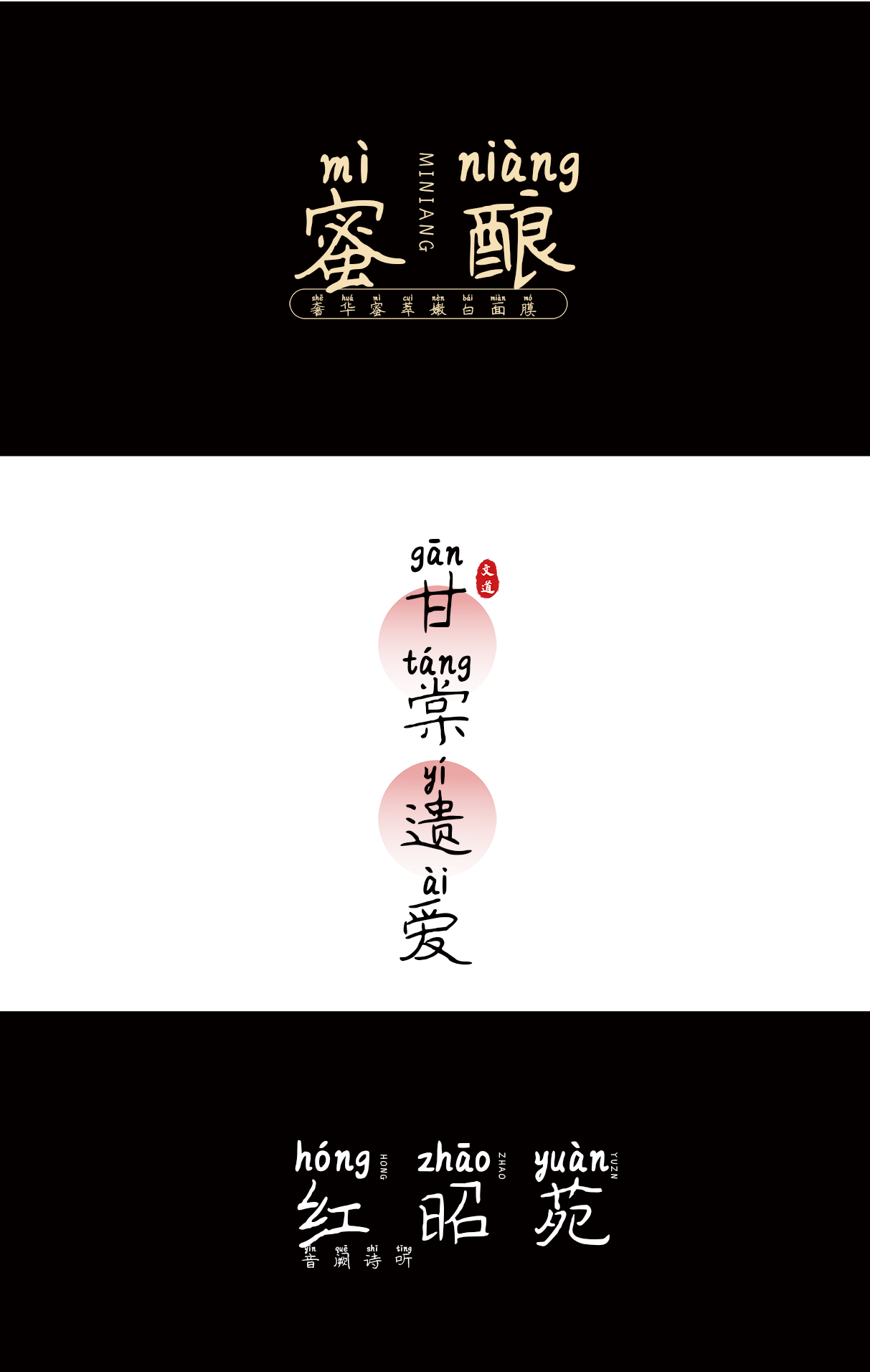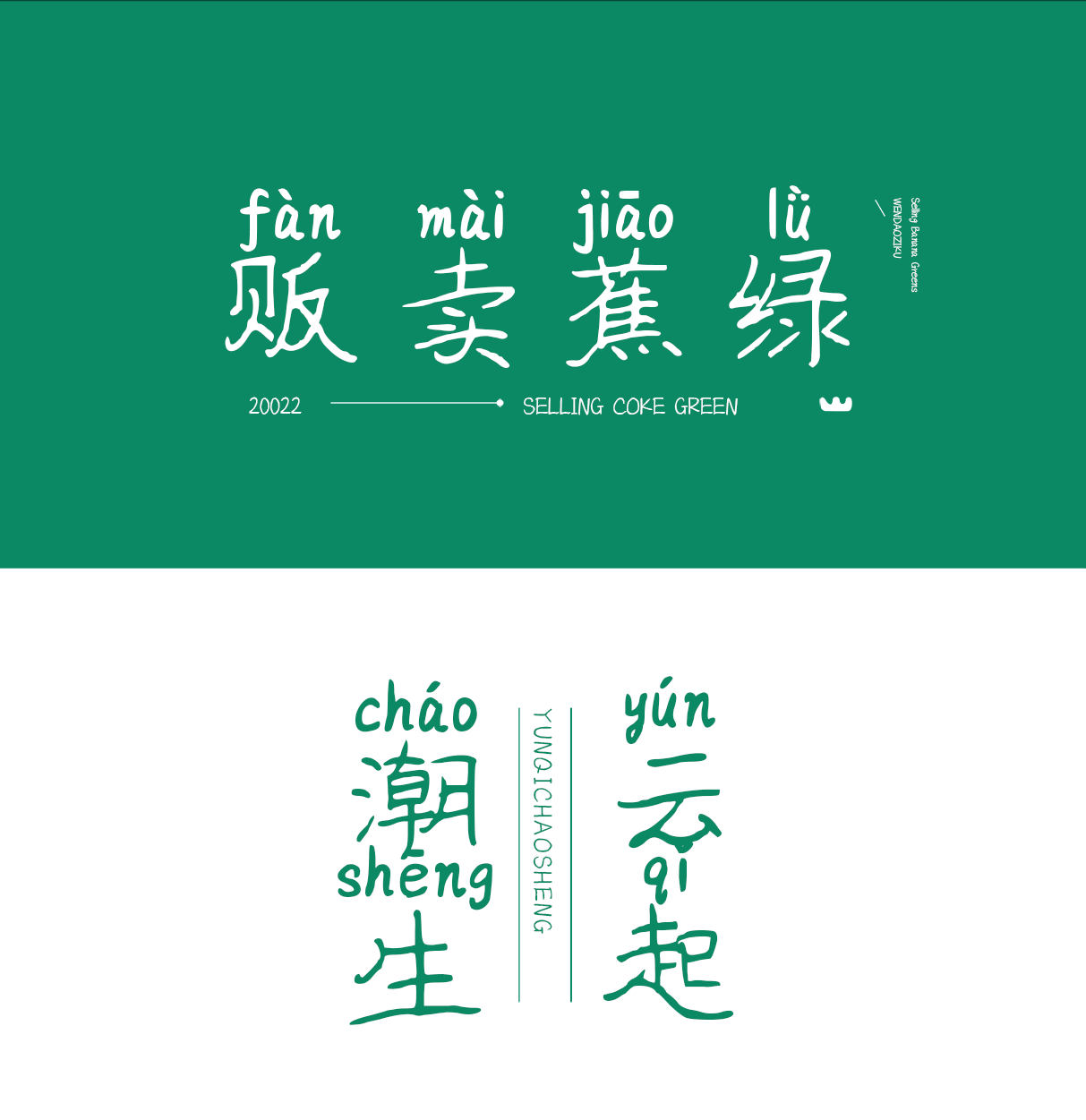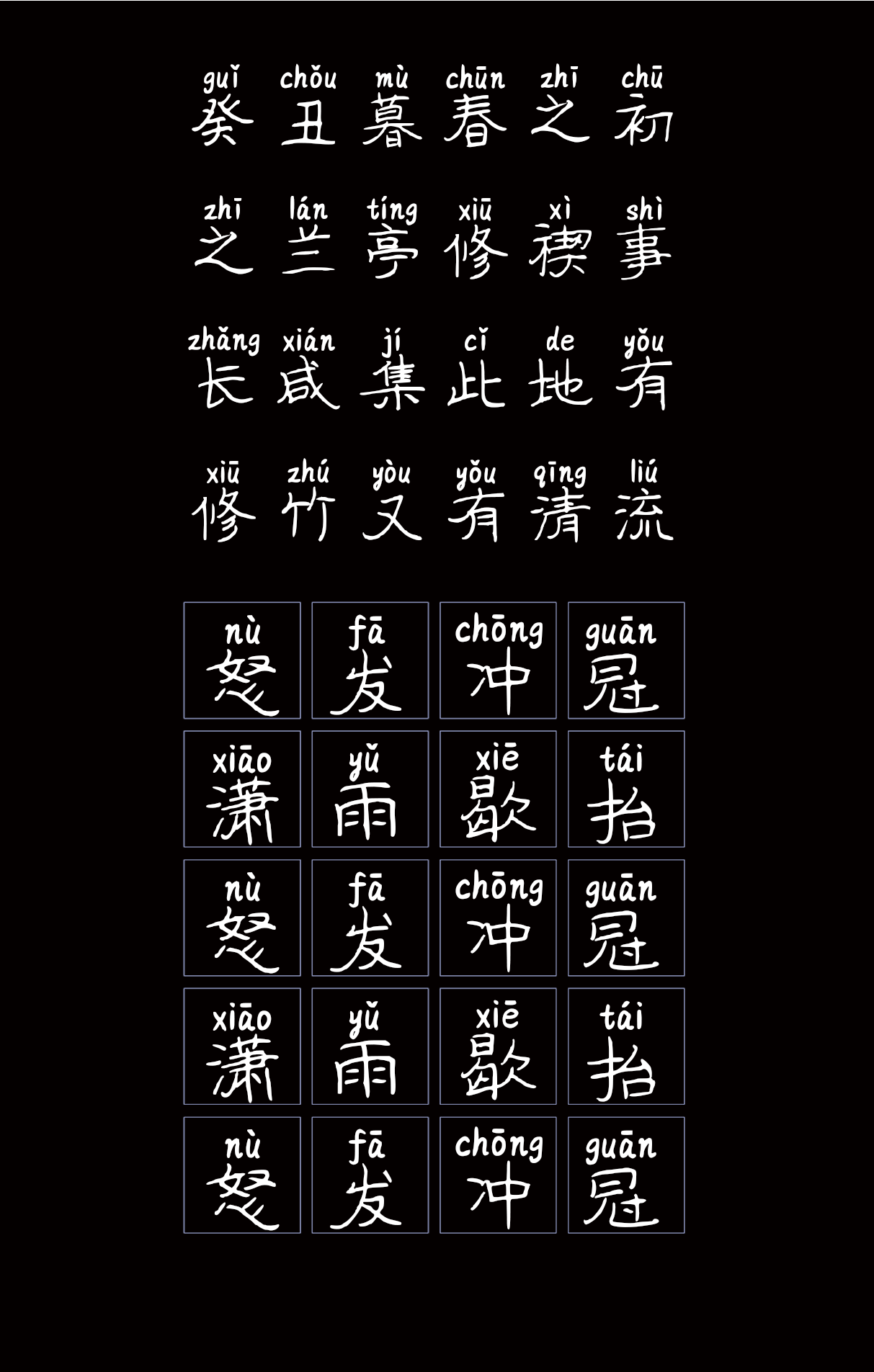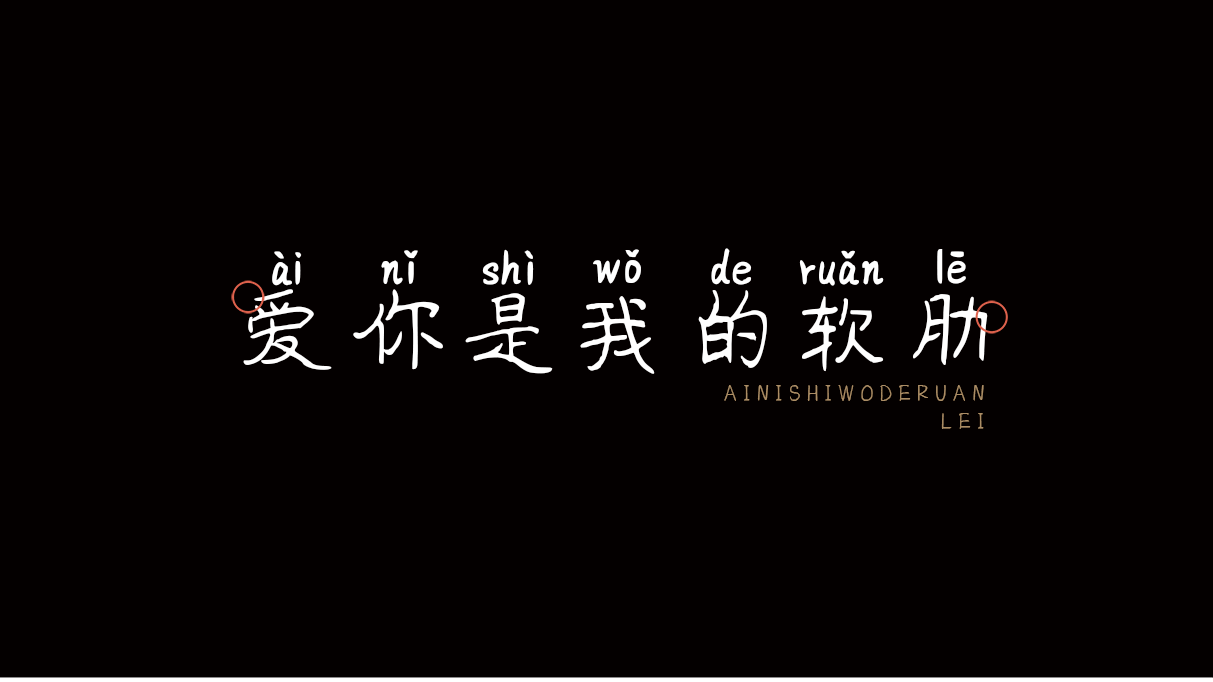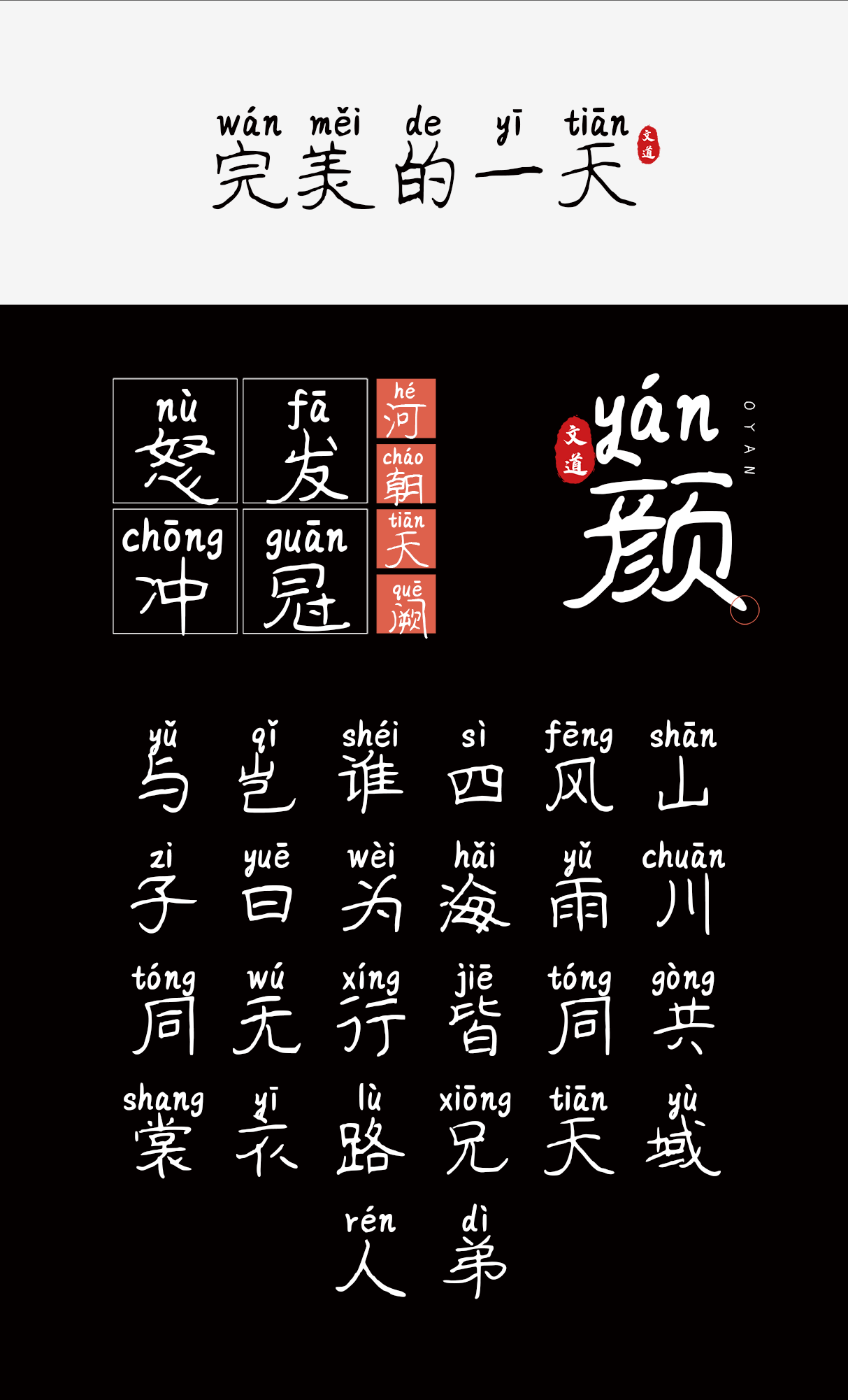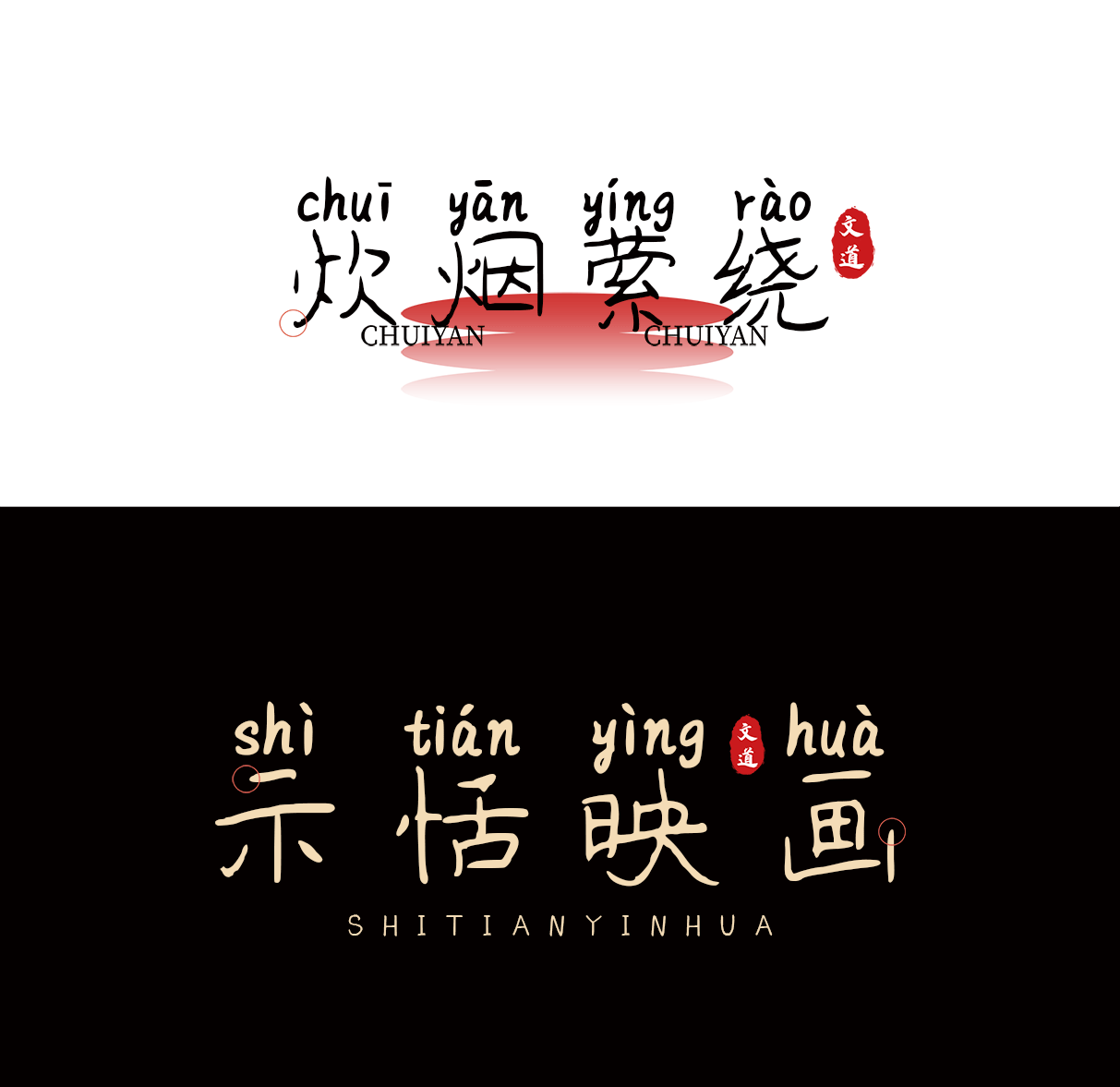
爱你是我的软肋
字体名称: 爱你是我的软肋
所属分类: 拼音体 隶书 硬笔手写
字符集: 简体字符
适用场景: 广告 电商 新媒 综艺 海报 印刷
简介: 21克拉的心这款字是一款自带拼音的创意字体,字体笔画简洁有张力,整体字体风格偏扁类似隶书,增添了一定的书法感觉。适用于印刷类广告和产品包装设计,也可适合相关创意海报的制作。